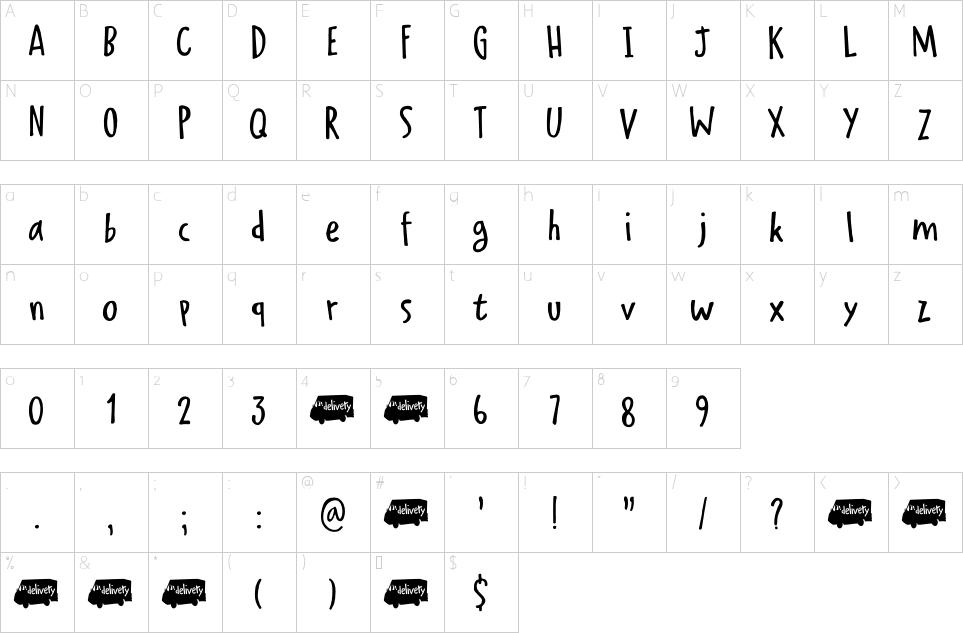
Aqui está uma descrição curta para a página de download da fonte ‘Delivery Note Font’, com um tom informativo e convidativo: O Delivery Note Font é uma elegante solução de fontes criada pelo designer Hanoded, disponível tanto para uso na versão Windows quanto Mac. Essa fonte foi projetada especificamente para relatórios de entrega, garantindo legibilidade e estética apropriadas em documentos importantes. Com um design minimalista e funcional, ele é ideal para empresas que buscam uma solução gráfica moderna para suas necessidades empresariais. Os usuários notaram sua facilidade na geração de notas de entrega digitais ou impressas, tornando-o uma fonte indispensável para quem busca qualidade sem comprometer a estética da escrita. Estamos orgulhosos em informar que o Delivery Note Font já foi baixado 13.406 vezes por profissionais e estudantes do design de todo o mundo, demonstrando sua relevância e popularidade como uma fonte gráfica gratuita. Download gratuitamente a partir de nossa plataforma hoje para adicionar esse recurso visual poderoso à sua produção de documentos comerciais ou escolares.